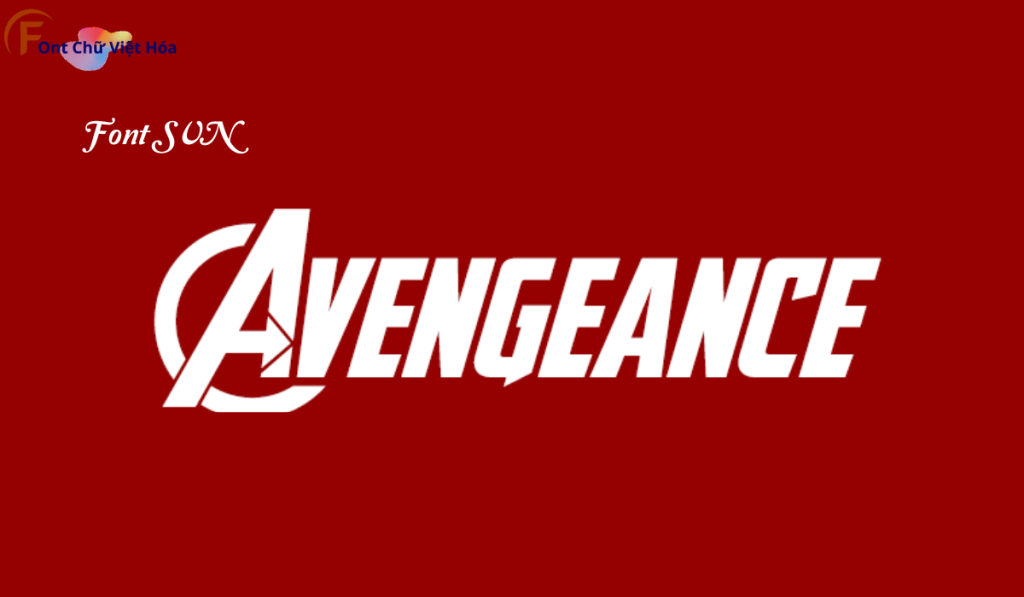
Font SVN Avengeance Việt Hóa
Phân loại: Cá tính, Độc đáo, Mạnh mẽ
Độ dày: Thường
Font SVN Avengeance Việt Hóa là một font chữ không chân mạnh mẽ, thuộc bộ font SVN. Được thiết kế với mục tiêu mang lại sự nổi bật và ấn tượng, font này lý tưởng cho các dự án thiết kế như tiêu đề, quảng cáo, và bao bì sản phẩm. Với các nét chữ đậm và chắc chắn, Font SVN Avengeance Việt Hóa không chỉ dễ đọc mà còn tạo cảm giác mạnh mẽ và quyết đoán. Việc Việt hóa font giúp người dùng dễ dàng sử dụng trong các thiết kế tiếng Việt, mang lại sự tiện lợi và thẩm mỹ cao.